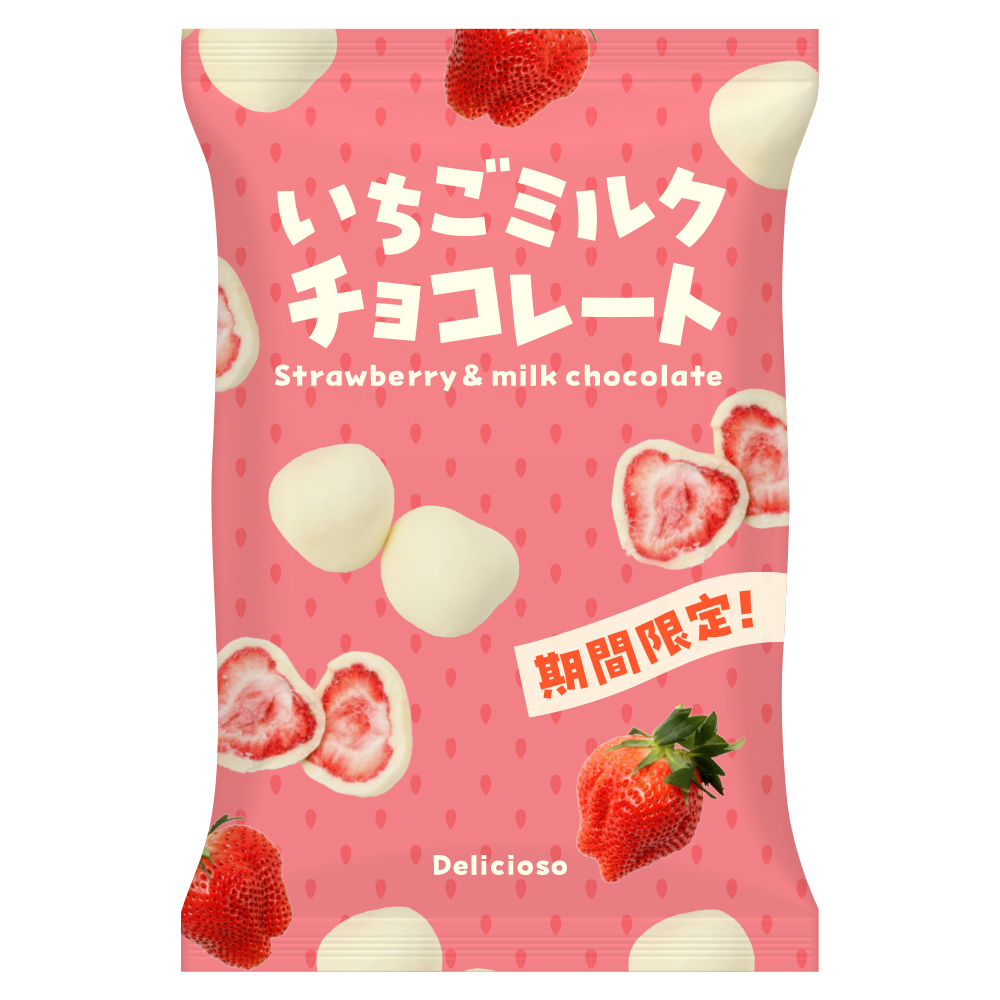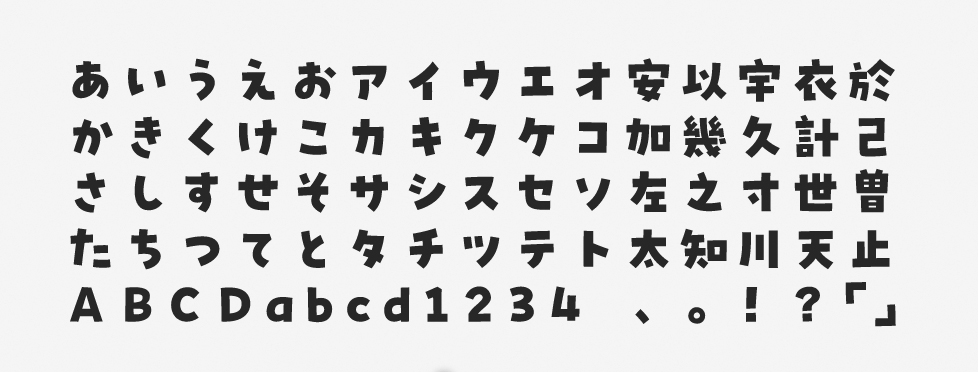
「プフ ピクニック」について
プフ ピクニックは2022年秋の新書体としてリリースされた人気の「プフシリーズ」の1つです。同シリーズは統一しすぎない自由な字形や小さめの字面が特徴で、このほかにもプフ マーチ、プフ ホリデー、プフ ポッケなどがあります。プフ ピクニックは、手書きのようなストロークで表現された極太のゴシック体テイストのデザインです。
「プフ ピクニック」の特徴
はつらつとした明るい雰囲気を感じさせ、パッケージやポスターのほか、動画テロップなどでも使いやすいフォントです。丸ゴシック体と比べるとどこかカッチリした真面目な印象が加わるため、単に可愛いだけでなく「楽しそうでありながらも誠実」といった微細なニュアンスの表現に役立ちます。
また、本フォントには「プフシリーズ」に特有の “隠し要素” も含まれています。独自のキャラクター絵文字を1文字だけ収録しており、異体字として選択入力が可能です。
手描き風のストロークのプフ ピクニックは、元気・活発といったイメージが強いデザイン書体です。作例のようにベースラインを崩し、少し回転をかけて文字どうしが踊っているような加工をして使っても面白い効果が得られるでしょう。